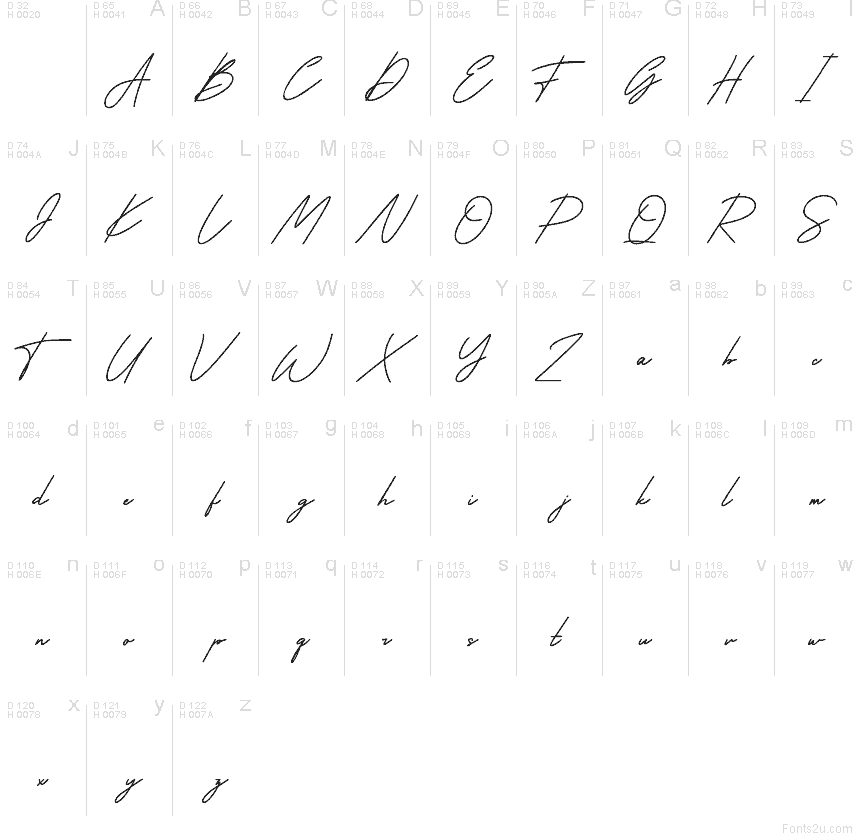
American Signature, da Essentials Studio, é uma fonte gratuita de estilo manuscrito com um ritmo leve e fluido, e um toque pessoal distinto. As letras combinam traços longos e fluidos com ligações estreitas e rápidas, fazendo com que a fonte pareça um autógrafo feito à mão com confiança, em vez de uma caligrafia excessivamente polida.
É perfeita para branding, embalagens de beleza, artigos de papelaria para casamentos, assinaturas em redes sociais e linhas de destaque em boutiques onde um nome ou frase curta precisa daquele toque autêntico feito à mão. Sendo uma fonte gratuita, é especialmente útil para logotipos, cartões de título e monogramas, já que os traços de abertura estendidos e as letras finas e conectadas dão a quantidade certa de movimento a palavras curtas.